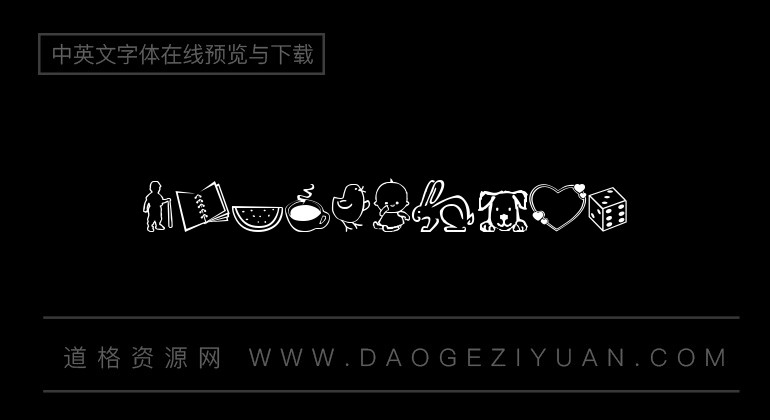
ScrapiCons
ScrapiCons是一种免费的矢量图标字体,由Juan Pablo del Peral创作。它包含超过160个图标,涵盖了各种类别,如社交媒体、货币、文档、设备、电子邮件、食品、时尚、健康、家庭、音乐、自然、人物、运输和天气。这些图标都是以手绘风格为基础创作的,具有简单而独特的设计风格。 ScrapiCons字体可用于许多设计项目,如网站设计、移动应用程序、印刷品和演示文稿等。此外,ScrapiCons字体是完全免费的,并且可以在多种格式中下载,包括ttf、otf、eot、svg、woff、woff2和css。
ScrapiCons是一款非常不错的手写艺术字体,具有很好的视觉感,适合于文化类的宣传设计、商业类品牌的广告和产品包装设计以及个性化文字排版等较多场景。